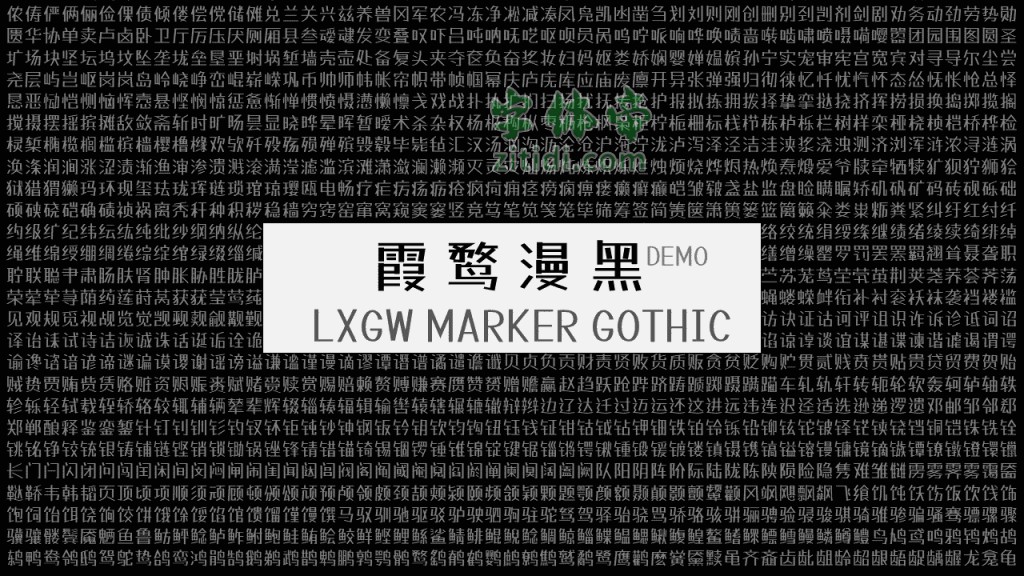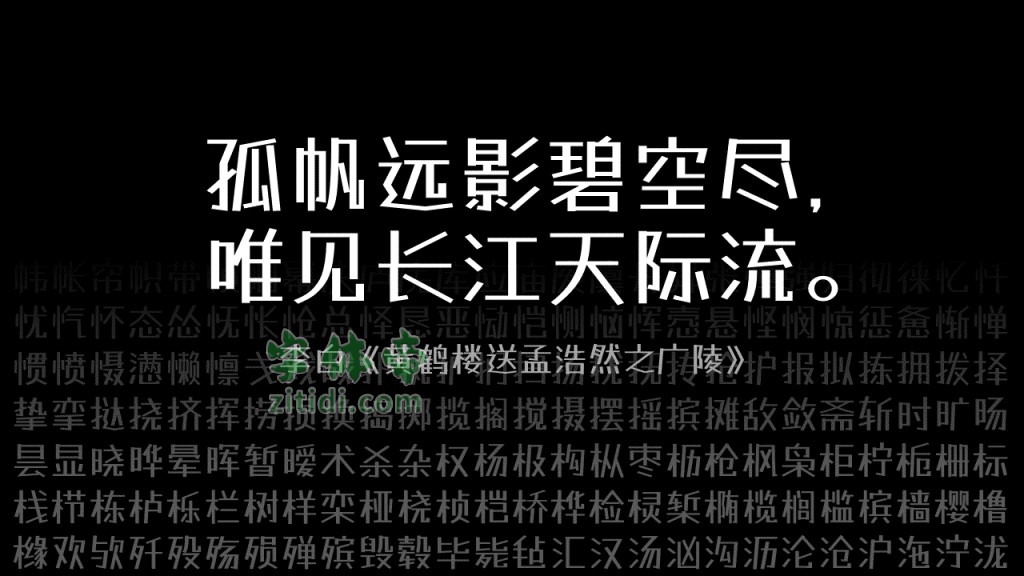
霞鹜漫黑是一款由 Tanugo手写体衍生的开源中文字体。本字体是基于 たぬゴ角 改造的具有马克笔书写风格的中文字体,可用于漫画、广告等用途。目前在原有 JIS 第一/二水准字库的基础上,已补完原字体中所含的繁体字对应的简体字,及 3500 常用字。
简体部分
- 补完原字库中含有的繁体字对应的简化字;
- 补完 3500 常用汉字 ①;
- 通用规范汉字表一表 3500 字,修改字形;
- 补完 GB2312。
① 又名「现代汉语常用字表」。
繁体部分
- 补完台湾 4808 常用字 ②;
- 补完 GB/T 12345-90;
- 补完常用粤闽客字。
② 又名「常用国字标准字体表」。